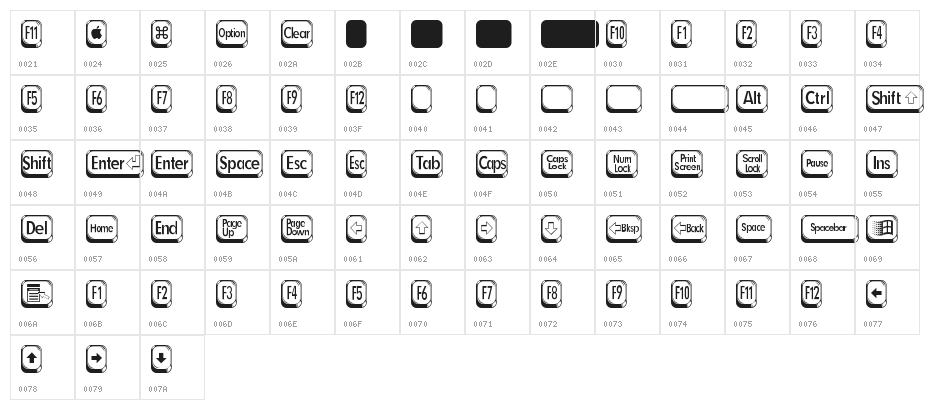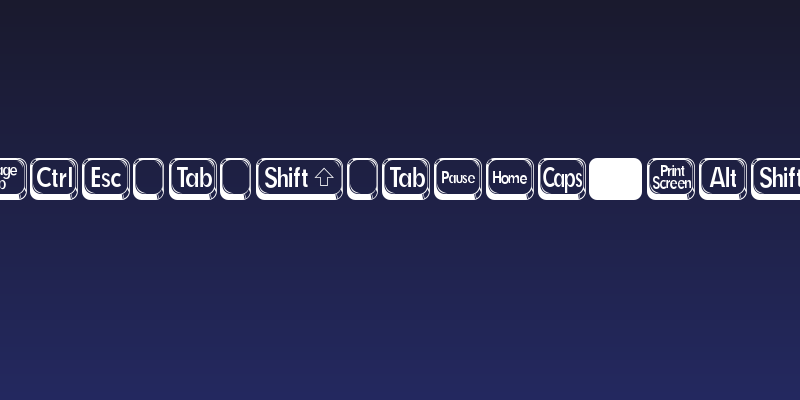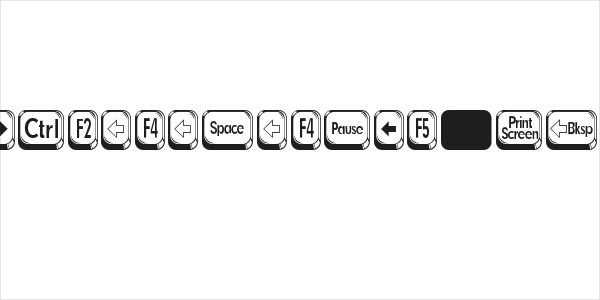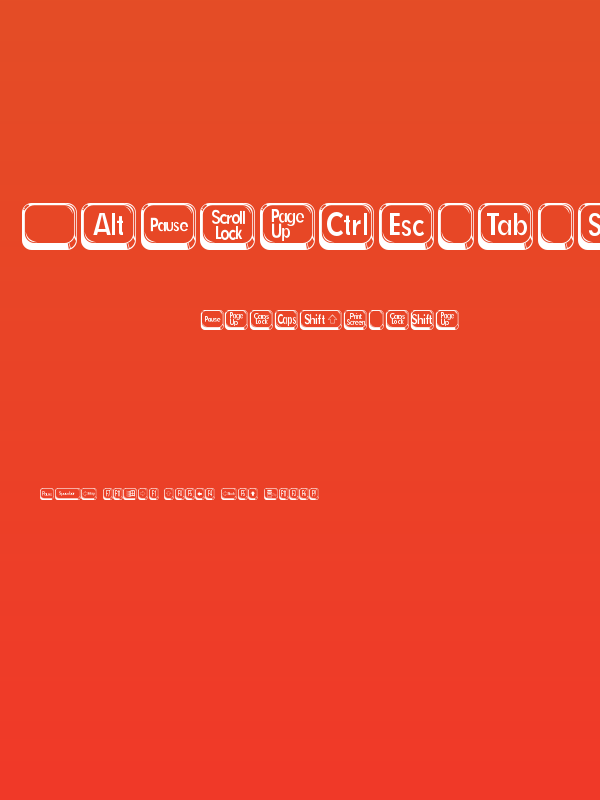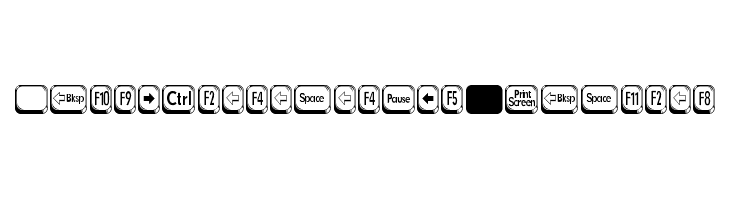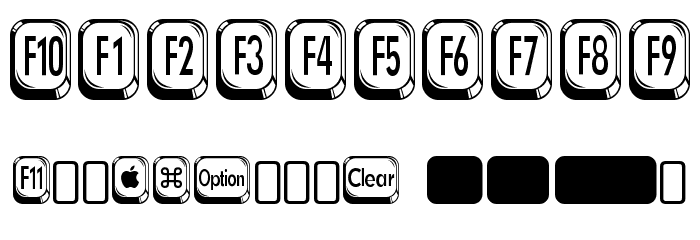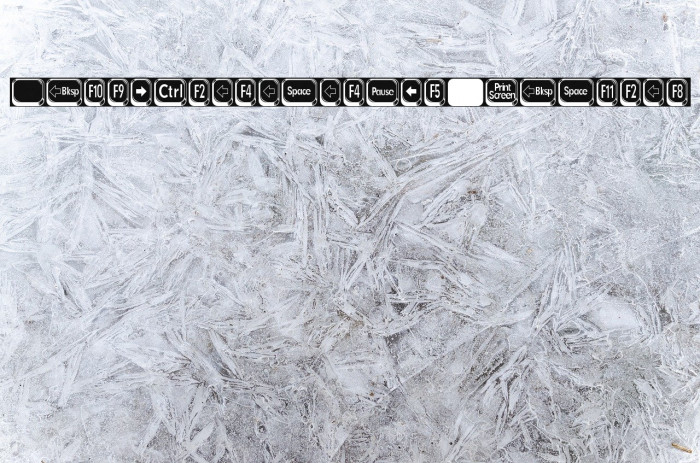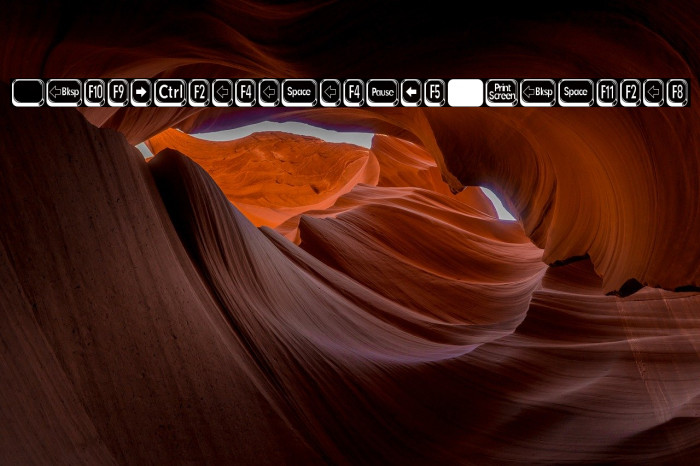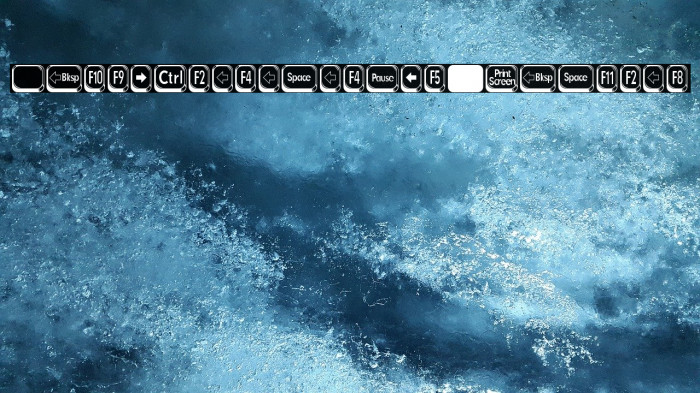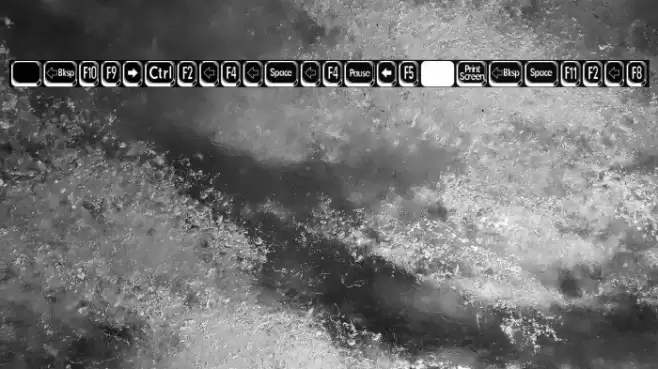
BetsyFlanaganTwo-Regular Font
| Caso de uso | Logos, Digital interfaces, Educational materials |
| Projetos propostos | Ideal for tech-themed designs, educational materials, digital interfaces, and retro computing projects. |